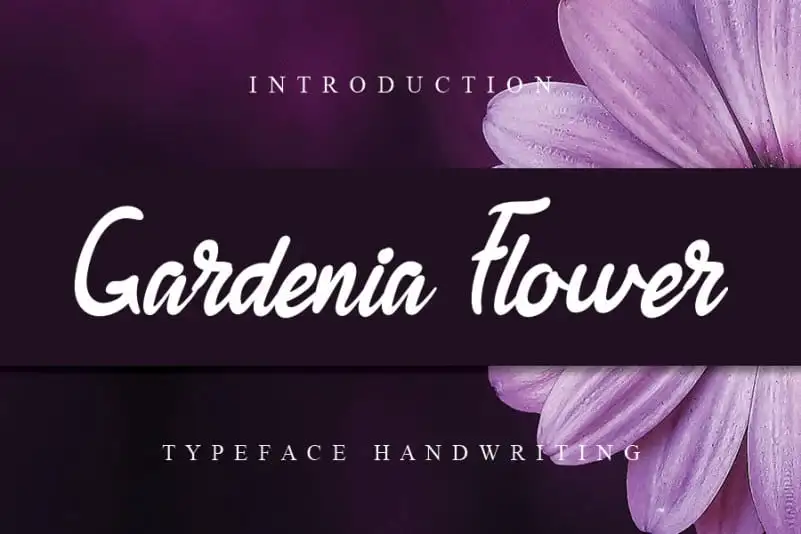
Gardenia Flower Script Font – Download Grátis
Gardenia Flower Script Font é uma elegante fóntes casual escrita a mão que vai transformar seu trabalho em algo ainda mais realista e surpreendente. Ideal para quem deseja dar um toque único à suas ideias gráficas ou criações digitais, este fonte é perfeito para designers de qualquer nível. A sua forma delicada, com traços fluidos e detalhes suaves, oferece a liberdade criativa que você precisa para expressar o seu estilo próprio, enquanto mantém um equilíbrio elegante. Seja em projetos gráficos de design editorial, logos ou qualquer outra aplicação onde uma fonte escrita a mão pode dar um toque diferenciado ao trabalho final, Gardenia Flower Script Font é certamente uma opção que deve ser considerada para qualquer designer buscando algo inovador e único. Idealmente combinada com o Designer andikastudio, sua fóntes oferece uma mistura perfeita de elegância e originalidade, tornando-o um recurso imprescindível para quem está sempre à frente do seu tempo.